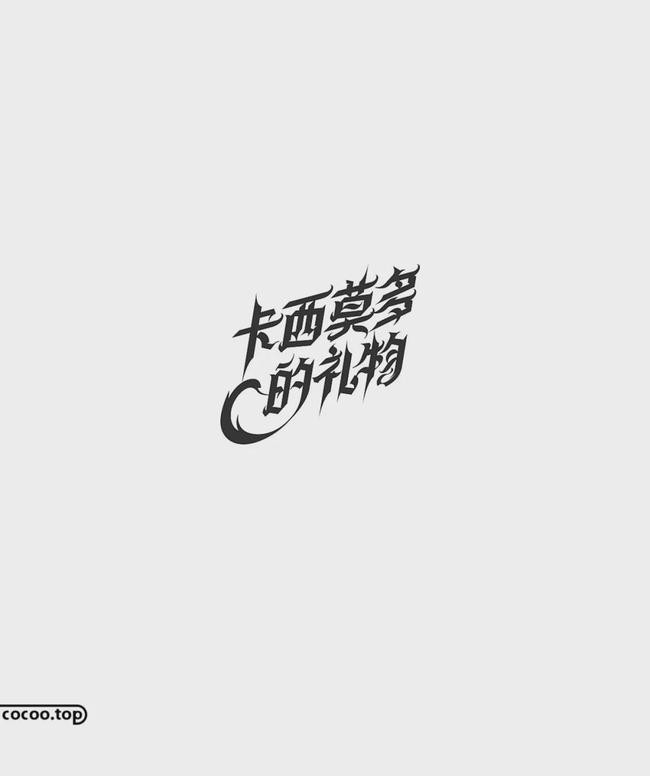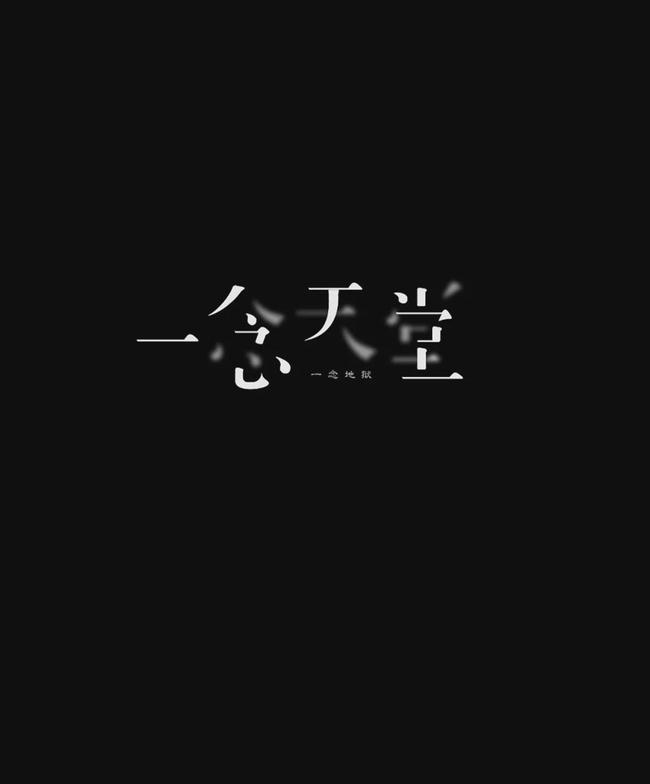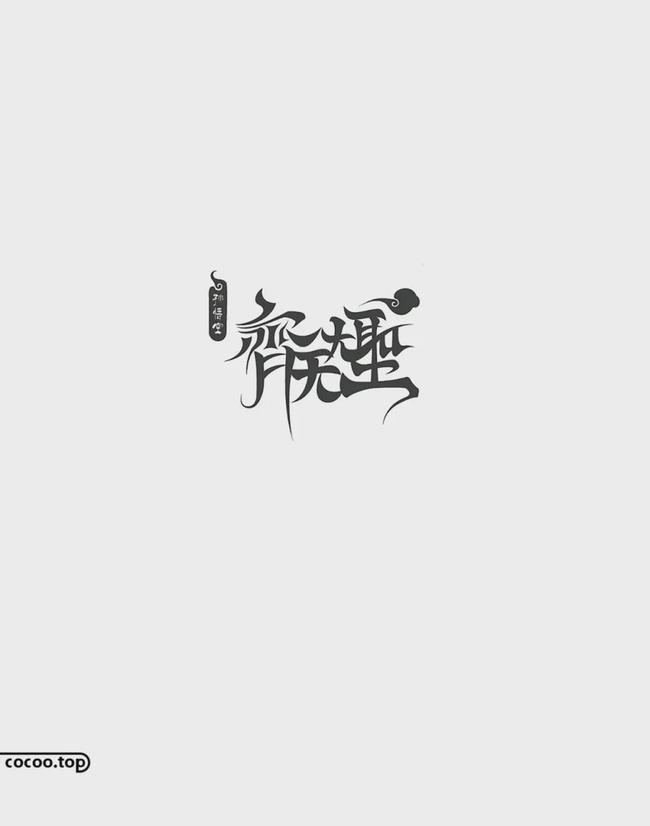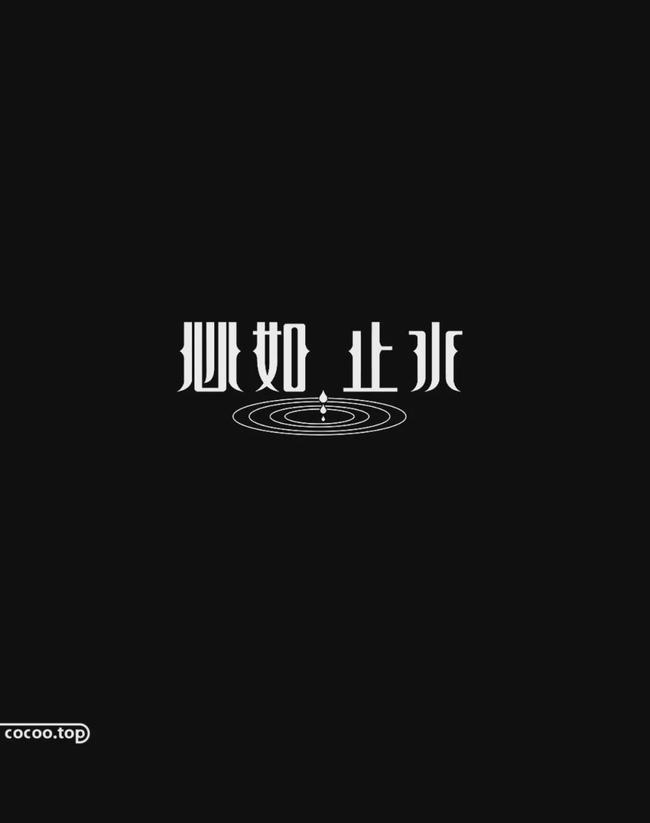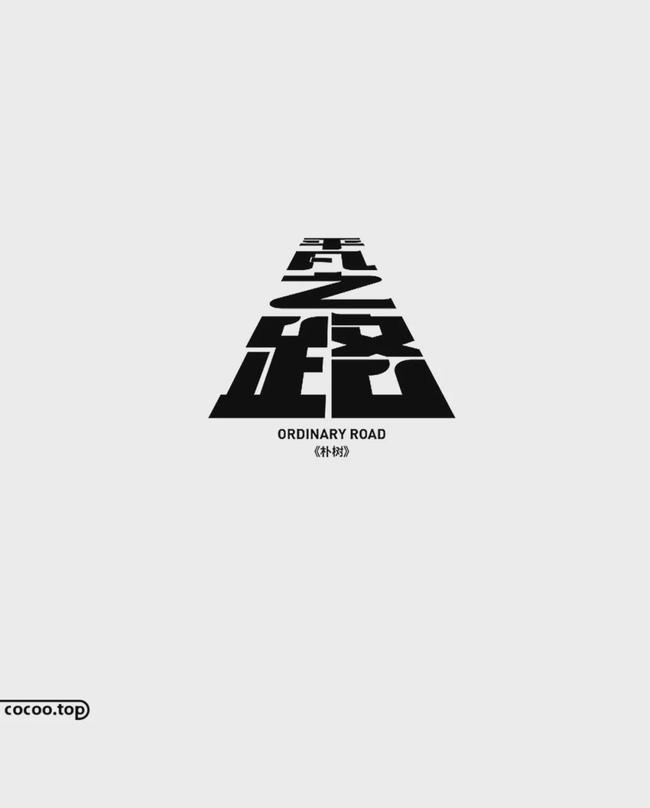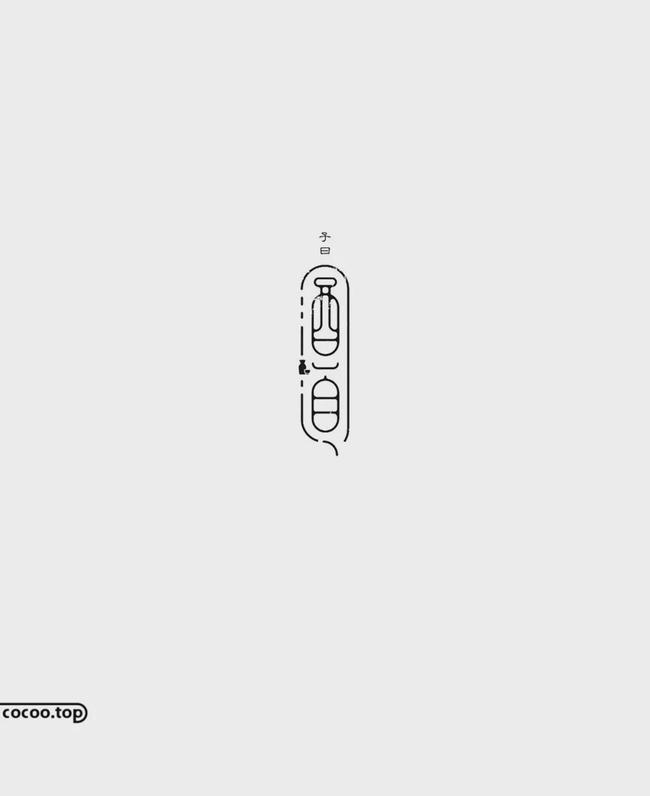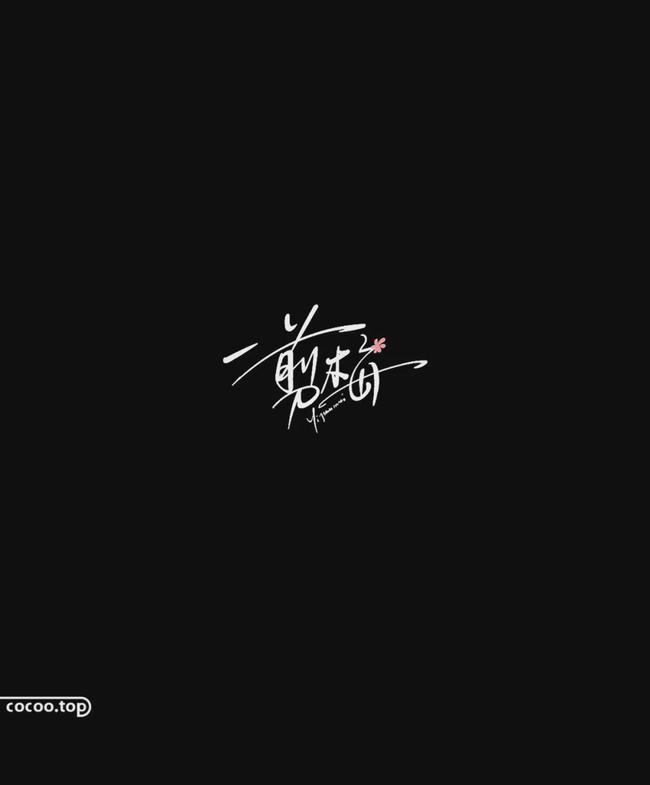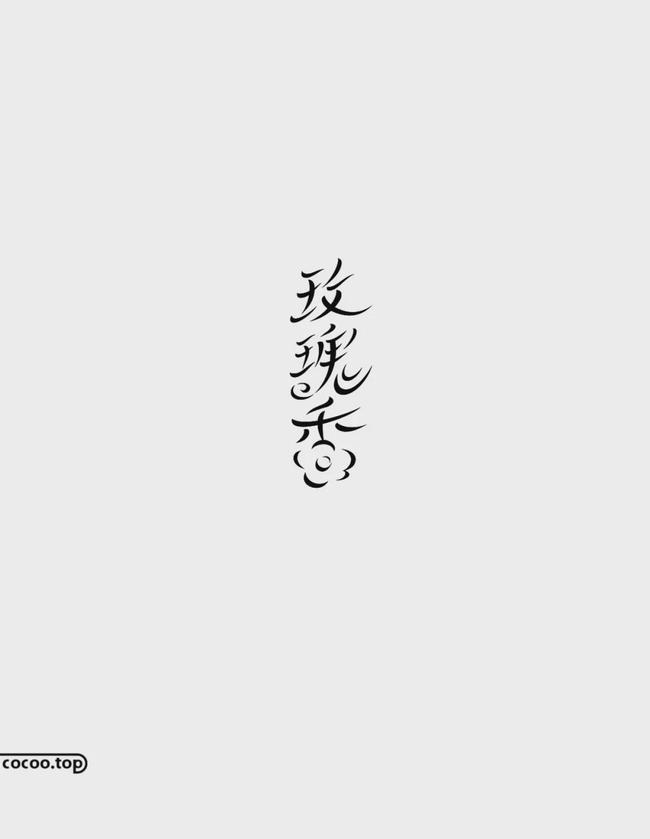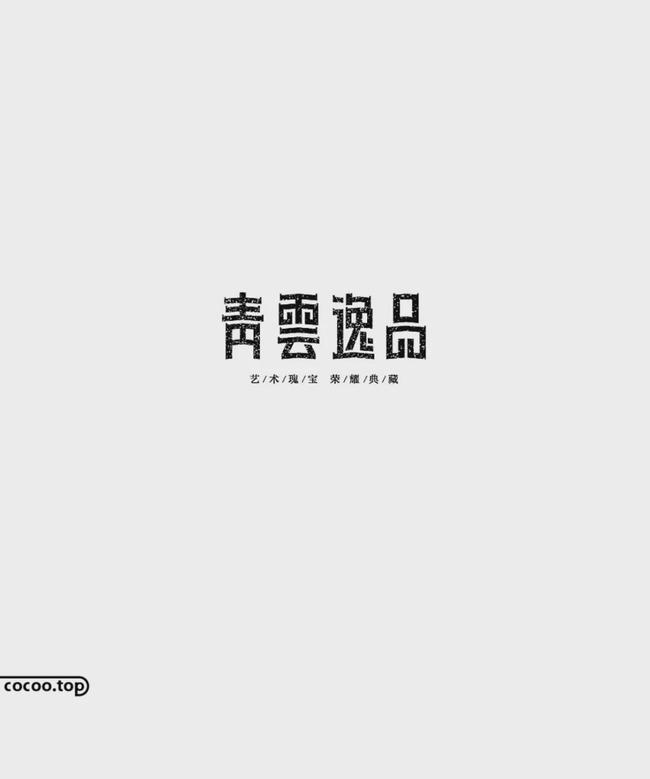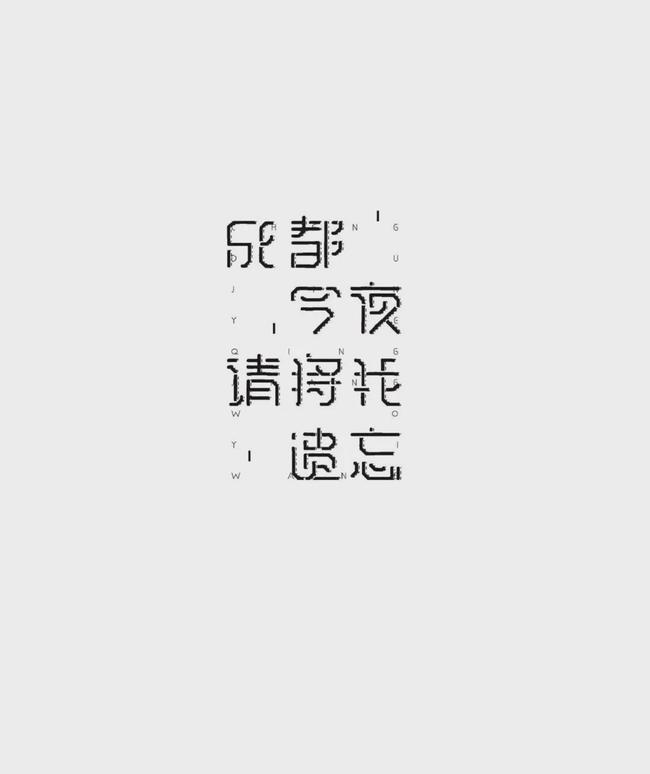
平面设计的工作几乎离不开文字,基本上所有的设计都会涉及具体的字形设计,不管是标准字还是美术字。有时候现有字库中的字体,使用前都需要改动,甚至重新设计,才能满足设计的要求。
其实,字体设计所牵扯的范围很大,我们并不需要去大量了解这方面的知识,我们可以把这个字体的范围缩小,变成一个将文字情感化、图形化的过程。
情感化
情感化是指将文字本身的意思、应用到设计的主题、设计师自身的情绪,形象地表现到字体设计当中。
字体是有情感的,怎样找到不同字体所传达的情感呢?例如:黑体是中性字体,本身并不带什么情绪色彩;宋体代表一种古典、古老、怀旧的情绪;书法体有张力、流畅,代表柔中带刚的情绪。
当我们在做设计时不知道用哪种字体,或者设计字体的时候不知道做成什么样子的时候,当我们没有方向、感到迷茫的时候我们可以尝试去带着自己的情感想这些东西,做深入的思考,列出关键词,准确地定位哪一种字体才是最合适的。
如果所做的东西实在找不到情感的切入点,这时候选择黑体可能是比较保险的做法。
图形化
图形化就是把文字这种抽象的东西转化成生活周边的一些比较直观的事物。例如:看见时间这两个字你就会联想到钟表;看到吃饭这两个字你就会想到碗和筷子;提起对话这两个字就会想到手机等等。
如何把字体做成图形呢:我们总结了一些常用的方法,替换法、共用法、叠加法、分解重构法、尖角法、横细竖粗法、简细法、联盟法、摆放法、卷叶法、方方正正法、上下拉长法、断肢法结构转变法、照葫芦画瓢法、俏皮设计法、画龙点睛法等。
关联法
例如:时间会联想到钟表;对话会联想到电话;爱情会想到心等等,想到这些有代表性的字时,要巧妙地把图形和字体本身相结合。
风格法
经过艺术化设计以后,可使文字形象变得情境化、视觉化,强化了语言效果,成为更具有某种特质和倾向性的视觉符号。字体设计最基本的准则是在追求字体变化的同时便于识别。
①硬。力道、坚实、冲击、厚重、硬朗、猛烈,这类字体气势突出,视觉冲击力明显,个性张扬有力,节奏分明,可以用于表现强烈的信心和勇气,表现凝聚力和号召力,给人视觉上的震撼。
②软。柔美、纤细、优雅、亲近、温和、飘逸,这类字体适合表现细腻情感,如情感类设计主题、女性设计主题、公益类设计主题等,通过柔美的曲线笔画,可以让自己得到更大程度的展现。
③旧。严肃、端正、正式、中性、规矩、传统、古朴、怀旧,这类字形在品牌类字体中比较常见,给人以饱满充实的信赖感和说服力,保持规则的字体外形,在字体内部进行适度的笔画修整,在严谨中求突破,在规矩中求创新。
替换法
替换法是在统一形态的文字元素中加入另类不同的图形元素或文字元素。其本质是根据文字的内容意思,用某一形象替代字体的某个部分或某一笔画。
尖角法
把字的角变成直尖、弯尖、斜尖、卷尖,可以是竖的角,可以是横的角,这样文字看起来会比较硬朗。
断肢法
把一些封合包围的字,适当地断开一口,或把左边断一截,或把右边去掉一截。重点要在能识别的情况下适当断肢,从而表现出它与众不同的特点来。
错落法
把左右排列改为左上左下、上下排列或斜排,就是一边高一边低,让文字错落有致。
方正法
把所有字的弯全改成横平竖直、四四方方的。特点是简洁鲜明,便于设计,对熟悉字体结构有很好的帮助。
横细竖粗
可以说是替换法的一种,把竖、横或折换成其他相反交替而成笔画简化,在字体中加入个人情感,可以明确创意方向,设计出适合自己的字体。
随意手写
原笔迹的手写体总给人以亲切的感觉,手写字每一笔都不可复制每一画都触景生情。
汉字设计一般步骤
1.选取基础字形。首先选取一种基础字体,作为基本字形。
2.尝试修改笔画。仔细地研究每一个笔画的改变形式,然后选择最合适的表现方法,这样可以让每一个笔画都默契地组成这个字体,完全符合字体的空间规则。
3.确定后细化调整。确定完成字体变形后,我们可以分步来进行细节的润色,调整字体的笔画分布和重心均衡。在选定了字体的风格形式后,再给笔画做相应的视觉梳理。例如:字间距、笔画之间的间距、整体字形的倾斜角度、特殊地方做圆角处理、添加笔刷等。
字体设计其实方法很简单,重要的是要多去练习,多去摸索。在这里可以告诉大家一个实用的方法来训练培养思维,那就是每天坚持动手写字体日记,用笔去勾勒各式各样的字体,追求创意尽量让自己不要写重复的样式。